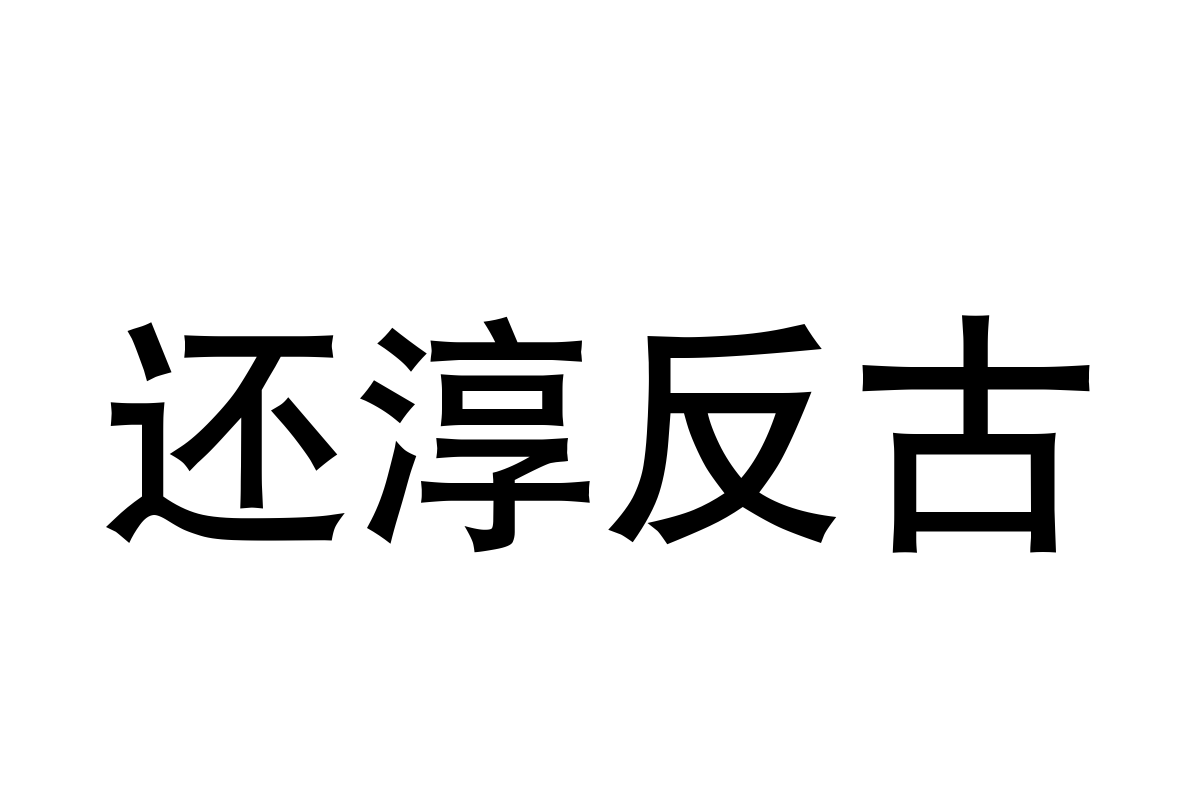
**汉仪中黑字体是一款由汉仪旗黑家族字体组成的字体,具有丰富的字重和广泛的应用范围**。
汉仪中黑字体是汉仪旗黑家族字体中的一员,它包含了长、方、扁三个系列字体,从细到粗共计15个字重。这样的设计使得汉仪中黑字体能够满足企业在多渠道、全方位内容设计上的需求,实现品牌形象的全方位覆盖。
汉仪中黑字体不仅适用于传统的书刊、画册、包装等设计领域,还广泛应用于现代的广告设计、海报制作、品牌标志设计等领域。其简洁大方的设计风格,使得字体在多种行业中的应用都显得游刃有余。例如,在报纸和杂志中,汉仪中黑字体以其优雅的外观赢得了广泛的认可;而在个性化的品牌标志设计中,它则能够有效地传达出品牌的独特性和识别度。
汉仪中黑字体的设计特点在于其流畅的使用体验和高度的适应性。它的字符分布涵盖了基本拉丁文、拉丁文-1补充、拉丁文扩充-A等多个语言字符集,并且考虑到了各种符号和标点的使用需求。这种全面性使得汉仪中黑字体能够在不同场合下都能保持良好的视觉效果和可读性,无论是用于正式的文件还是创意的广告设计。
综上所述,汉仪中黑字体以其丰富的字重、广泛的应用范围以及良好的设计特性,成为了设计师和企业在选择字体时的重要考虑对象。无论是作为商业广告的设计元素,还是品牌标识的一部分,汉仪中黑字体都能够提供专业的支持,帮助企业塑造独特的品牌形象。